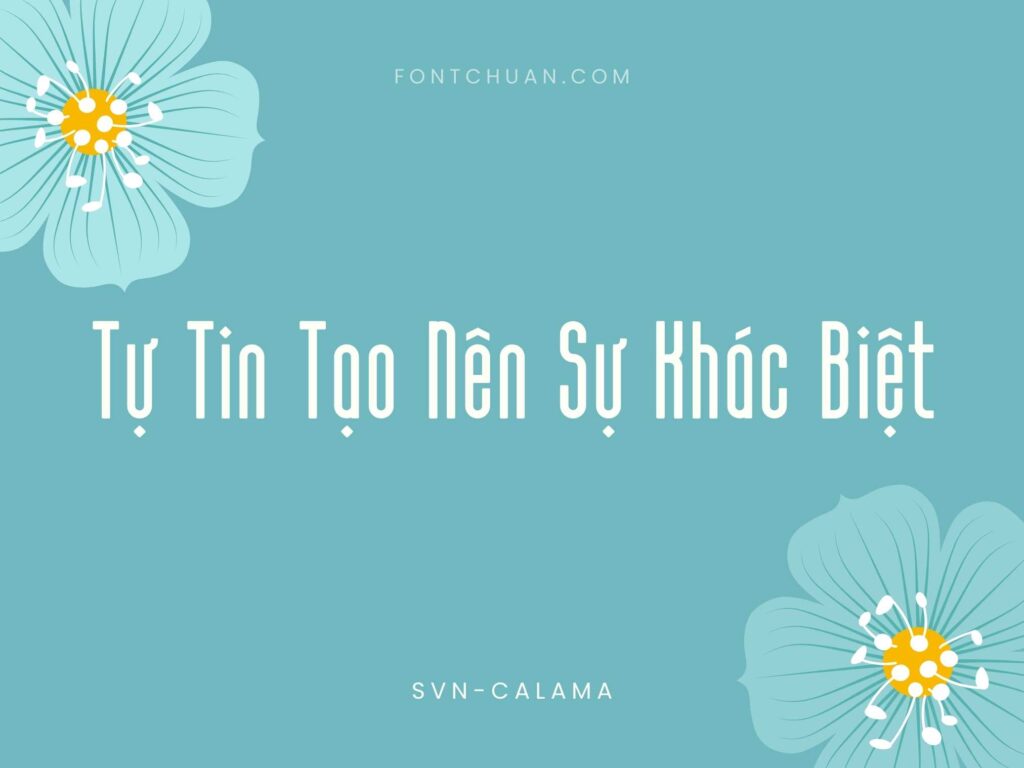
Font SVN Calama Việt Hóa
Tác giả Font: Ben Karamyan
Calama là một font chữ sans-serif hình học cô đọng với các góc bo tròn, được thiết kế bởi Ben Karamyan và phát hành lần đầu vào năm 2017. Font này mang lại sự hiện đại và tinh tế, phù hợp cho các tiêu đề, áp phích, tiêu đề và chú thích. Calama hỗ trợ nhiều ngôn ngữ, bao gồm cả tiếng Armenia, Latin và Cyrillic, giúp mở rộng phạm vi sử dụng trên toàn cầu. Font đã được Việt hóa để hỗ trợ tiếng Việt bởi Styleno.1 Fonts, đồng thời được thành viên của Font Chuẩn sưu tầm và chia sẻ, đáp ứng nhu cầu của bạn đọc và ứng dụng thực tế vào các dự án thiết kế.
Đặc điểm thiết kế của Calama bao gồm các đường nét cô đọng với góc bo tròn, tạo cảm giác hiện đại và sạch sẽ. Font này phù hợp cho các ứng dụng như thiết kế tiêu đề, áp phích, logo và các dự án sáng tạo khác. Các ngành nghề phù hợp bao gồm quảng cáo, công nghệ và giáo dục.